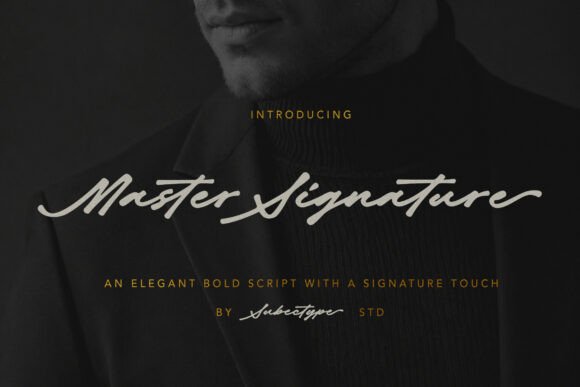
Master Signature
適切なデザイン要素を見つけるのは難しい場合がありますが、Master Signatureは作品を即座に引き立てる優れたコレクションを提供します。
POD(オンデマンド印刷)製品、結婚式の招待状、またはソーシャルメディアのグラフィックを作成している場合でも、Master Signatureは理想的です。